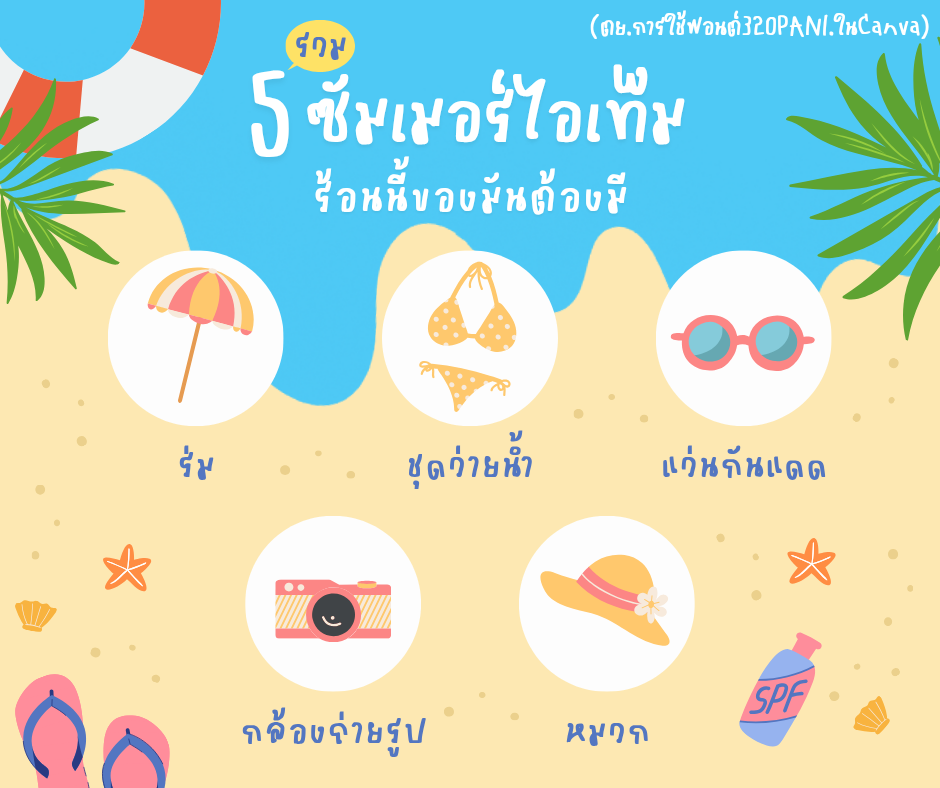
320PANI.Rainbow
PANI.
ฟอนต์ 320PANI.Rainbow
ฟอนต์แนววัยรุ่น ใช้งานง่าย เก๋ๆเท่ๆ
จะรายละเอียดเยอะๆก็อ่านได้
หรือจะแต่งคลิป แต่งภาพ ก็สมสมัยนิยม
แนะนำ สำหรับสายคอนเทนต์ค่ะ
ทำปกคลิป ทำปกคอนเทนต์น่ารักมาก
-น้องมีเลขไทยเป็นอีโมจิด้วยค่ะ
ใช้งานง่ายมากๆ แต่งง่ายเหมาะกับมือใหม่
ตัวอย่างการใช้งานใน Canva
แบบภาษาอังกฤษล้วน เท่ๆ